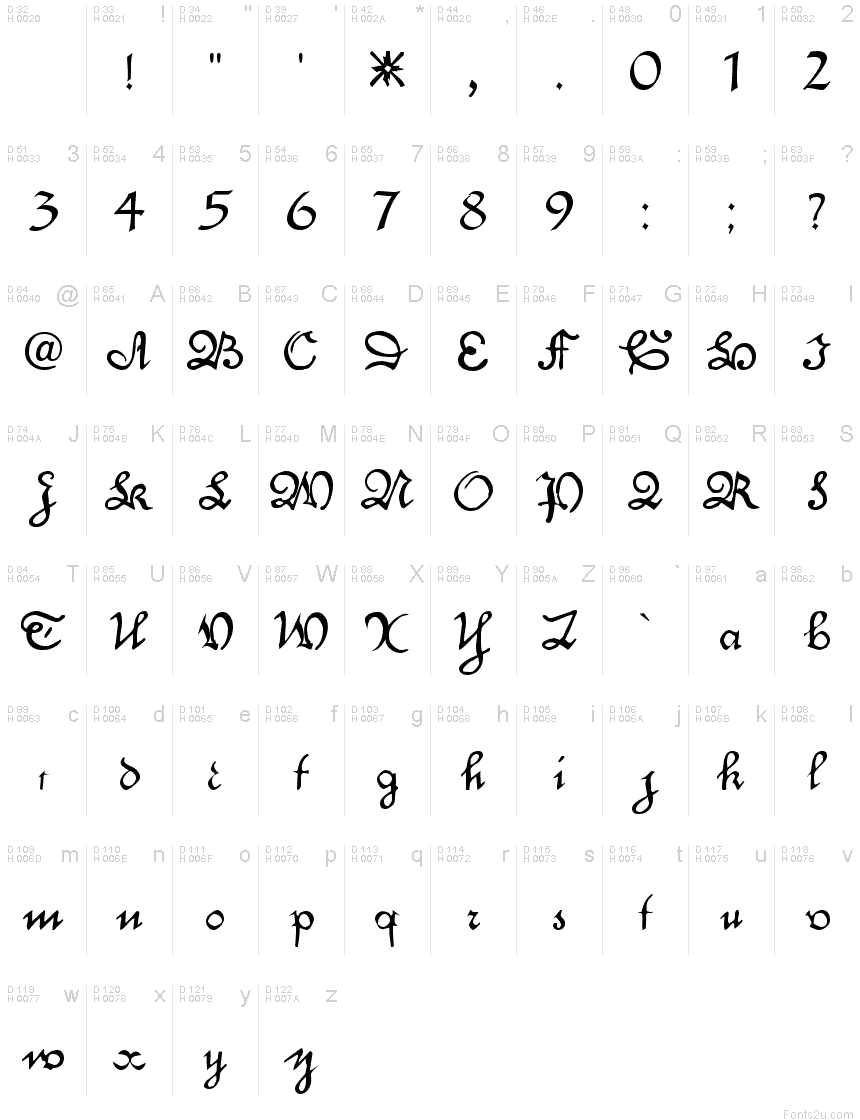
Engrossing, dzieło Davida F. Nallego z Scriptorium Font Library, to darmowy, odręczny krój pisma w stylu vintage, który sprawia wrażenie wyjętego prosto ze starego certyfikatu lub ręcznie wypisywanego dyplomu. Płynne pociągnięcia, atramentowe krzywizny i lekko nieregularne krawędzie nadają mu ciężaru i dramatyzmu tradycyjnej kaligrafii, nie czyniąc go przy tym sztywnym czy przesadnie formalnym. Litery łączą się w płynnym, teatralnym rytmie, który natychmiast dodaje każdemu projektowi odrobinę ceremonii i rzemiosła z minionej epoki.
Engrossing to darmowy font, który doskonale sprawdzi się na zaproszeniach ślubnych, dyplomach, okładkach książek, w brandingu retro, na plakatach wydarzeń, w logotypach oraz na opakowaniach w stylu historycznym. Wyrazisty charakter tego pisma najlepiej prezentuje się w dużych rozmiarach, gdzie jego loki i pętle mogą w pełni wybrzmieć. Zestaw go z czystym, subtelnym krojem szeryfowym lub bezszeryfowym w tekście głównym, aby zachować czytelność, pozwalając jednocześnie Engrossingowi grać pierwsze skrzypce w najważniejszych momentach projektu.